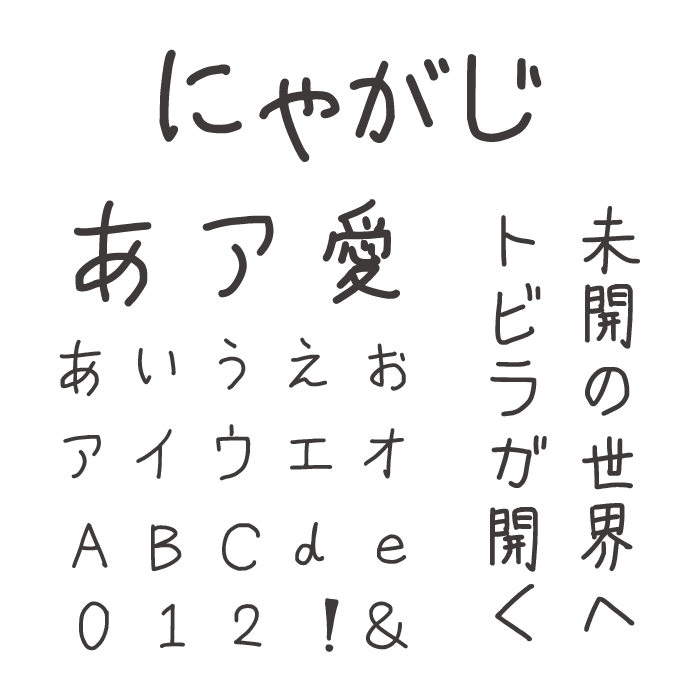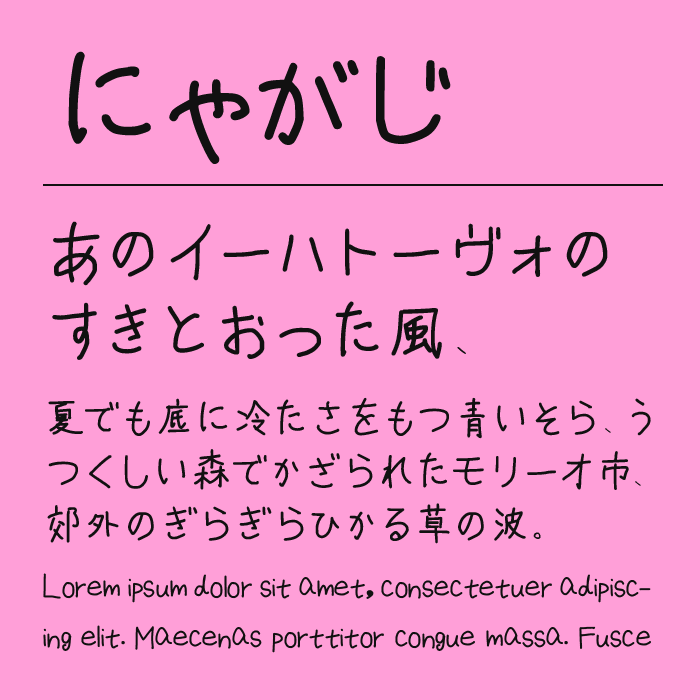
にゃがじフォントは、手書きのやわらかな線と、少し丸みを帯びたシルエットが特徴的な手書きフォントです。
線の強弱やわずかな揺らぎが自然で、まるでノートに気軽に書き込んだような親近感がある手書き文字です。ゆるさを持ちながらも文字の形は崩れすぎておらず、読みやすさを保ったまま温かい雰囲気を演出してくれるフォントです。
雑貨デザインやエッセイ風のレイアウト、カジュアルなSNS投稿などと相性が良く、見る人に安心感を与えるような空気感があります。日常にそっと寄り添うようなやさしいフォントです。
収録文字は、漢字・ひらがな・カタカナ・アルファベット・数字・記号が収録。